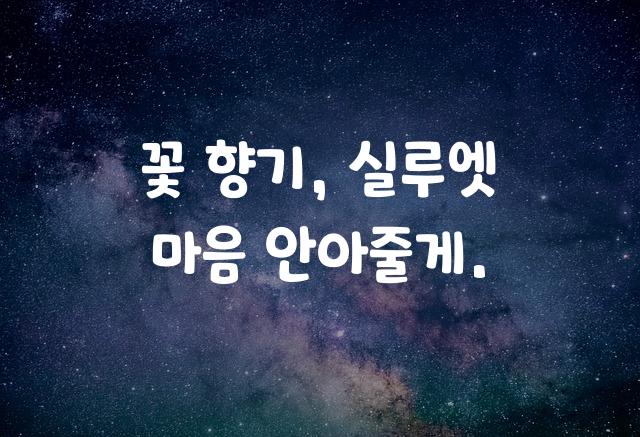
월영교체는 안동시에서 제작한 기본 고딕 폰트로, 제목용으로 최적화되어 있습니다. 깔끔하고 모던한 느낌이 강조되어 다양한 디자인에 효과적으로 활용될 수 있습니다.
월영교체은(는)
기본 고딕, 감성적인, 부드러움, 길고/크고 계열의 생김새를 가지고 있으며
출판 디자인, 제품 포장, 출판물 제목 등에서 자주 활용되며, 효과적인 메시지 전달에 적합합니다.
이 폰트는 출판/미디어, 문화/예술, 이벤트/웨딩 분야에 잘 어울리며,
전통적, 고급스러운, 클래식한 느낌을 담고 있는 것이 특징입니다.
이 폰트와 유사한 폰트로는 나눔고딕, 맑은 고딕, 돋움 등이 있어요. 함께 비교해 보시면 좋습니다!